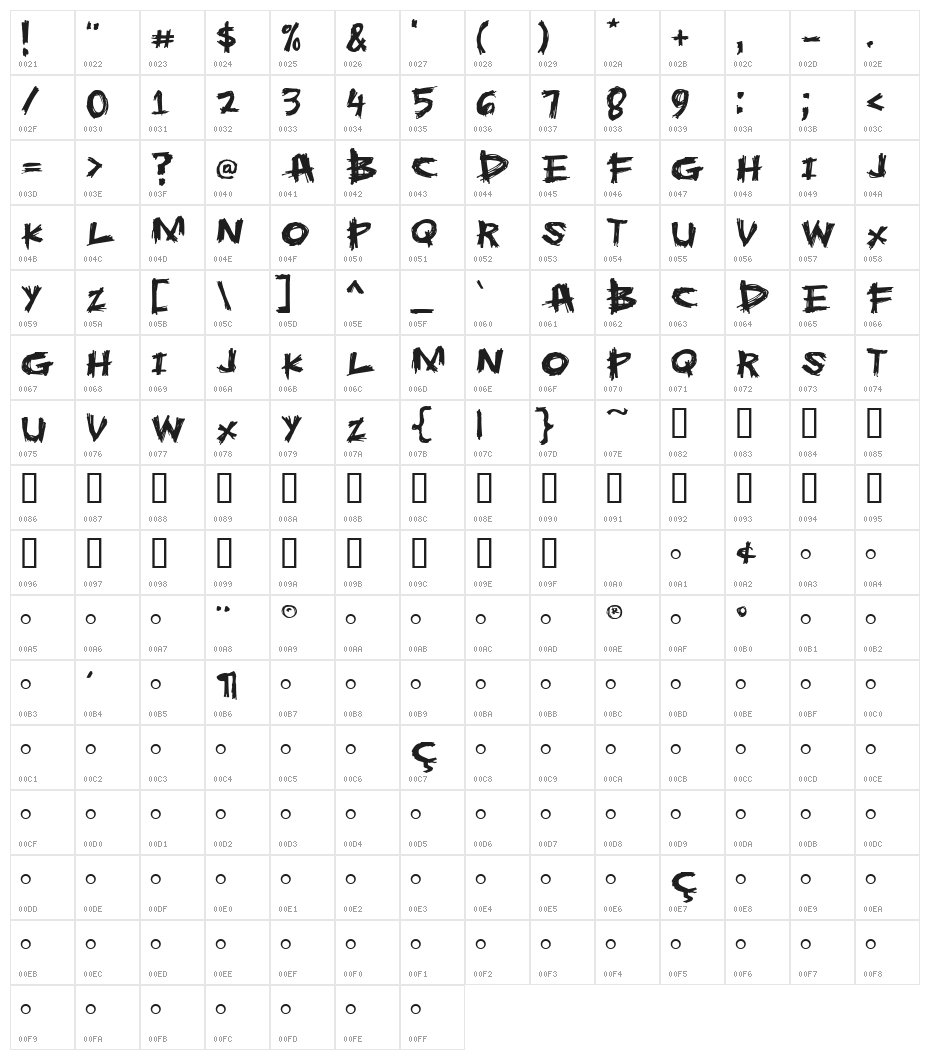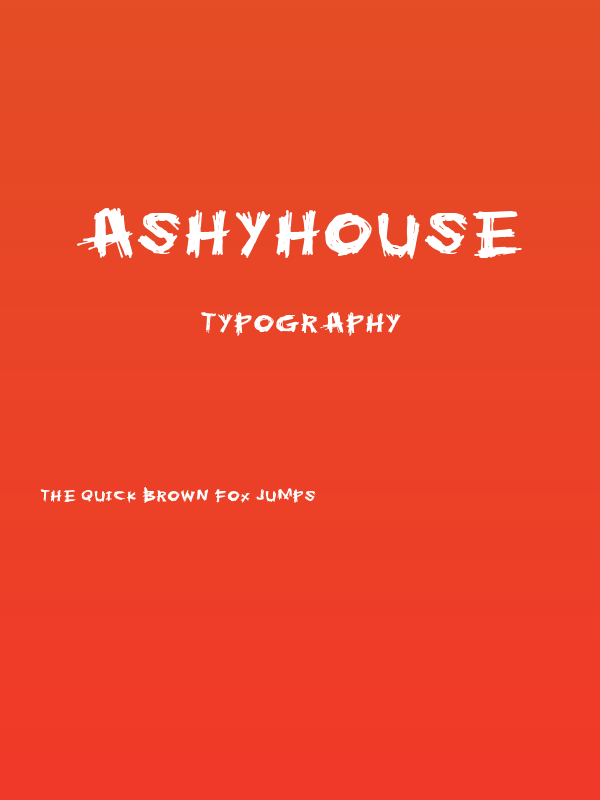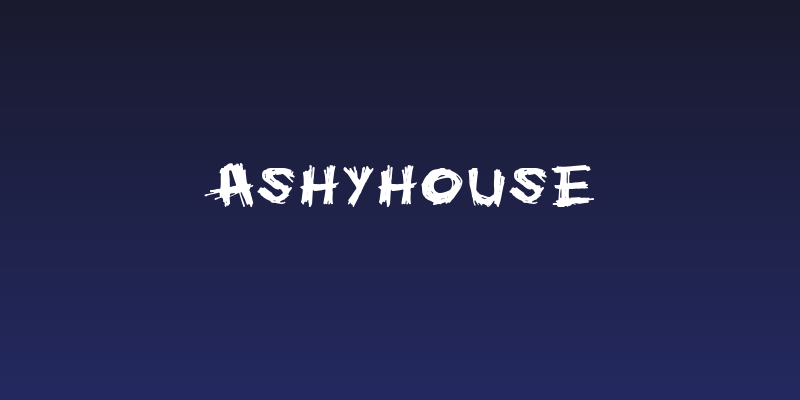
Ashyhouse Font
| श्रेणियाँ | Modern |
| चौड़ाई | Condensed |
| कंट्रास्ट | High |
| समग्र शैली | Decorative |
| उपयोग का मामला | Headlines, Logos |
| सुझाए गए प्रोजेक्ट | Perfect for album covers, posters, street art designs, and edgy branding projects. |